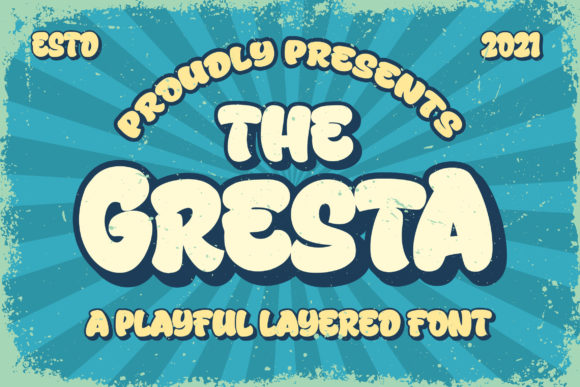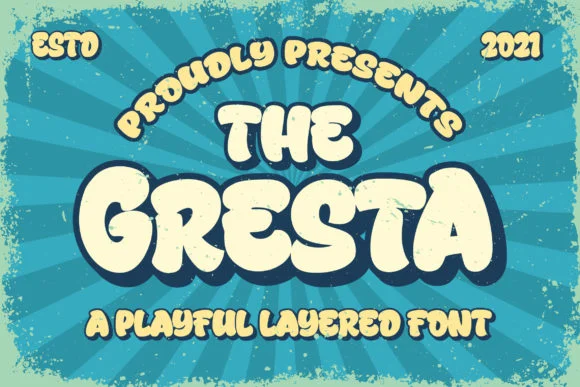
Название: Greasta Font (2021)
Gresta - это смелый, игривый и веселый шрифт.
Если вы используете его для дизайна, связанного с мультфильмами, детскими играми или просто для любого творения, требующего милого прикосновения, этот шрифт станет прекрасным выбором.